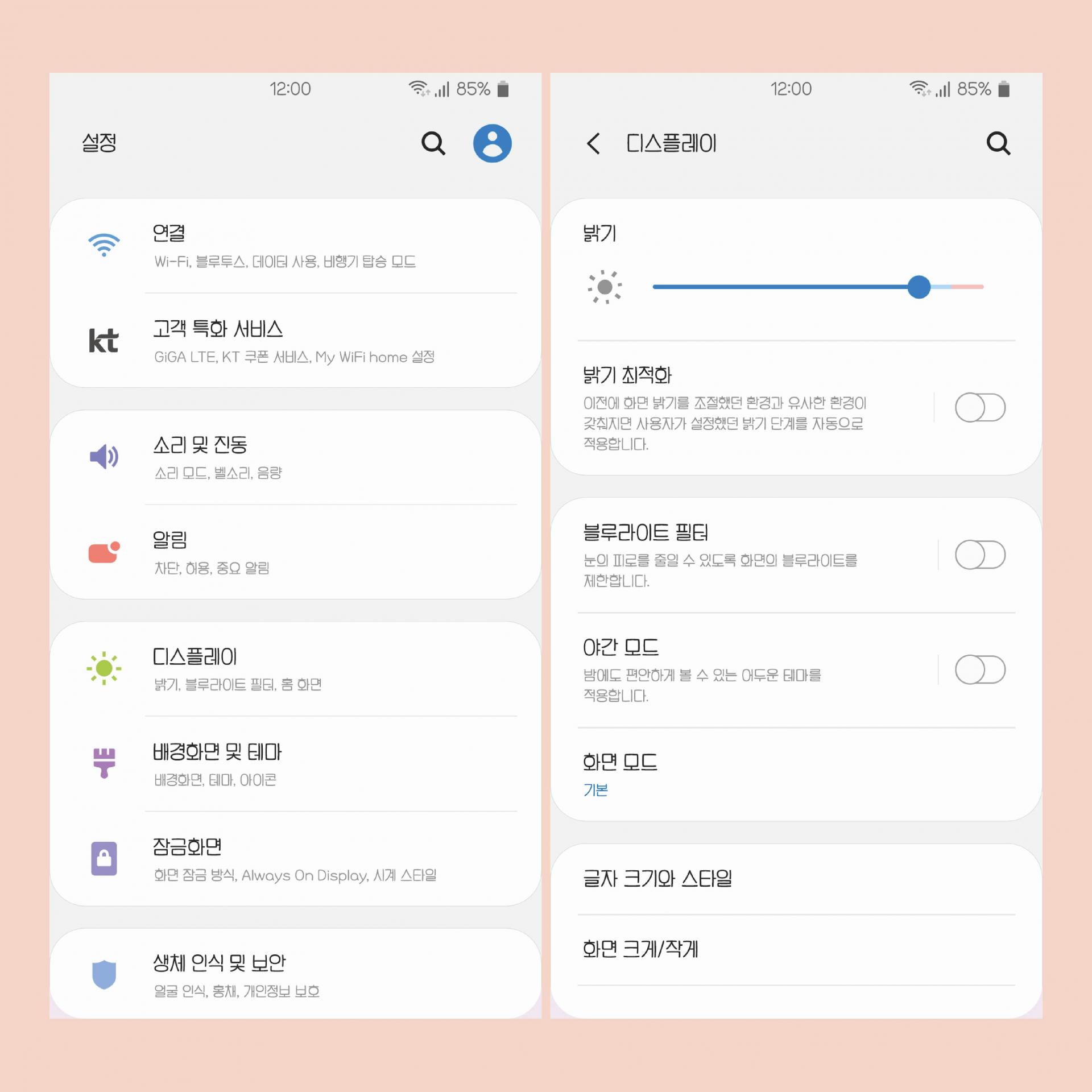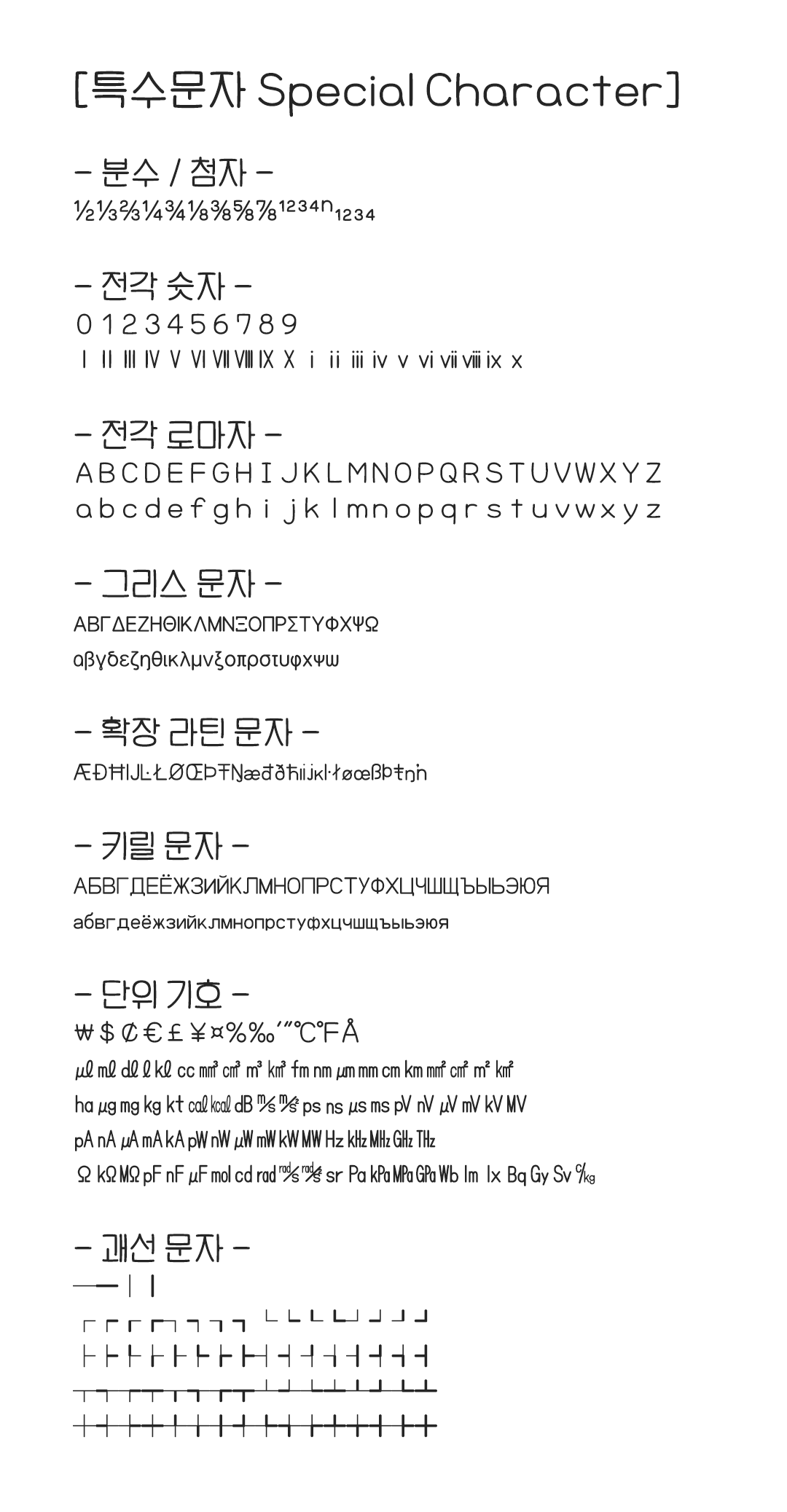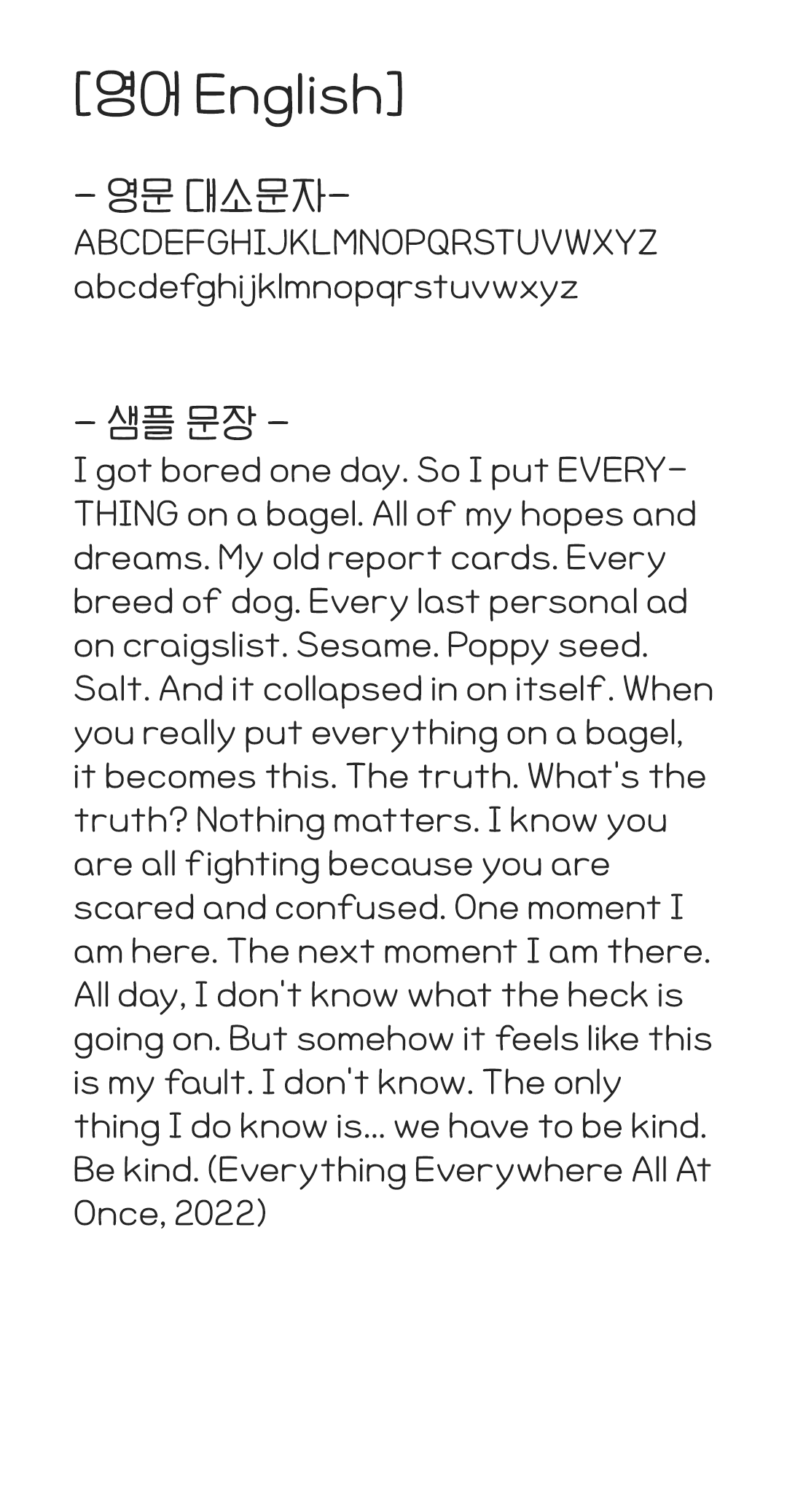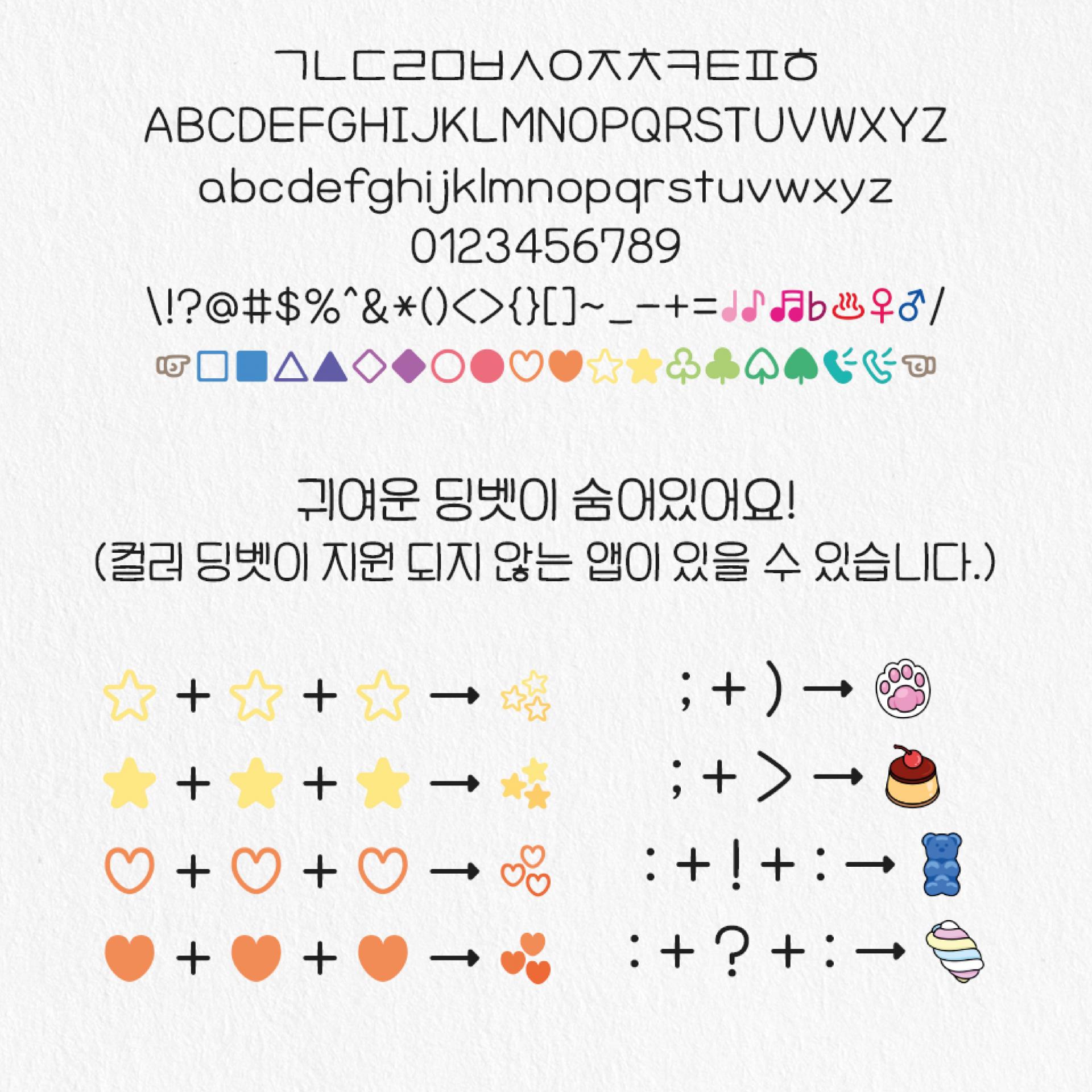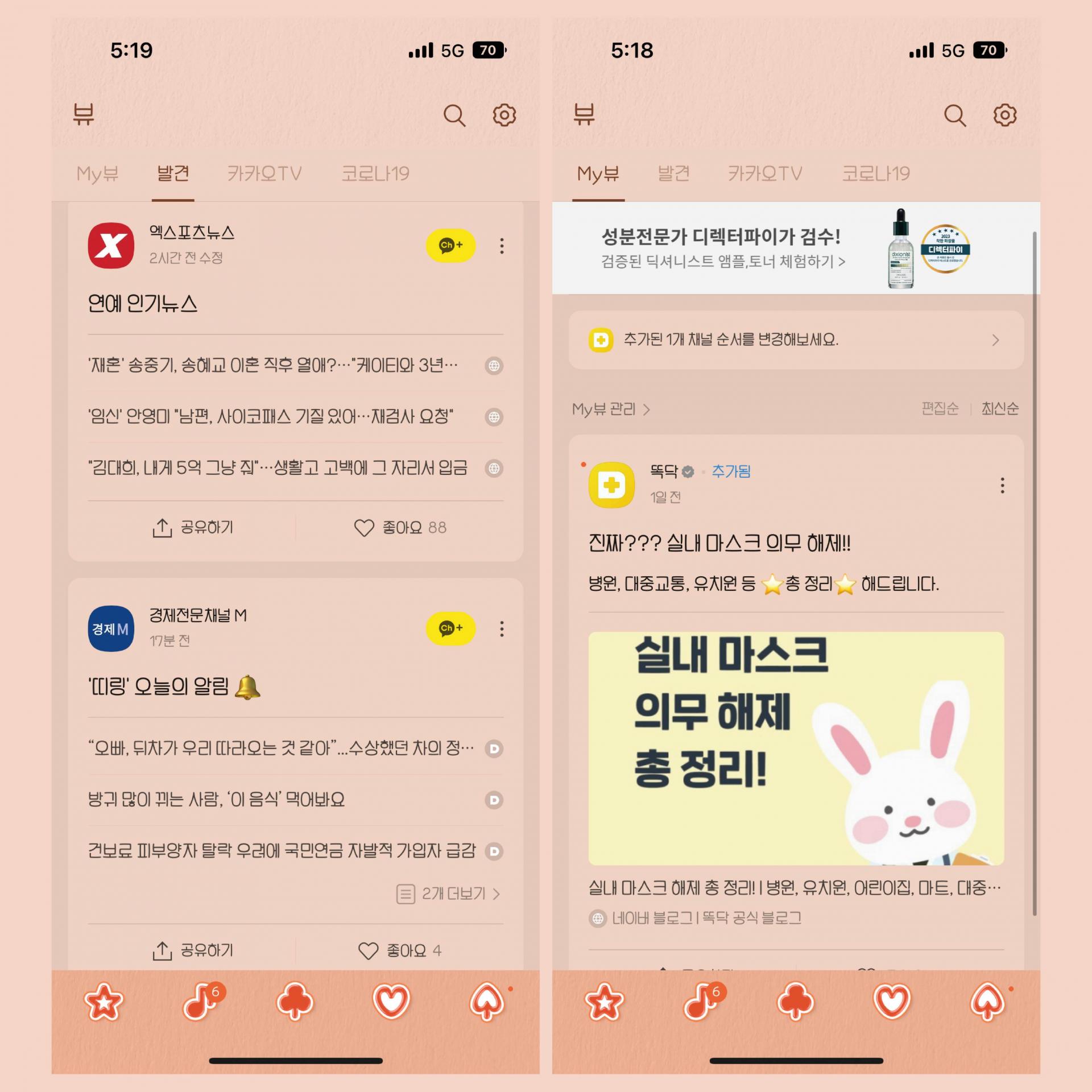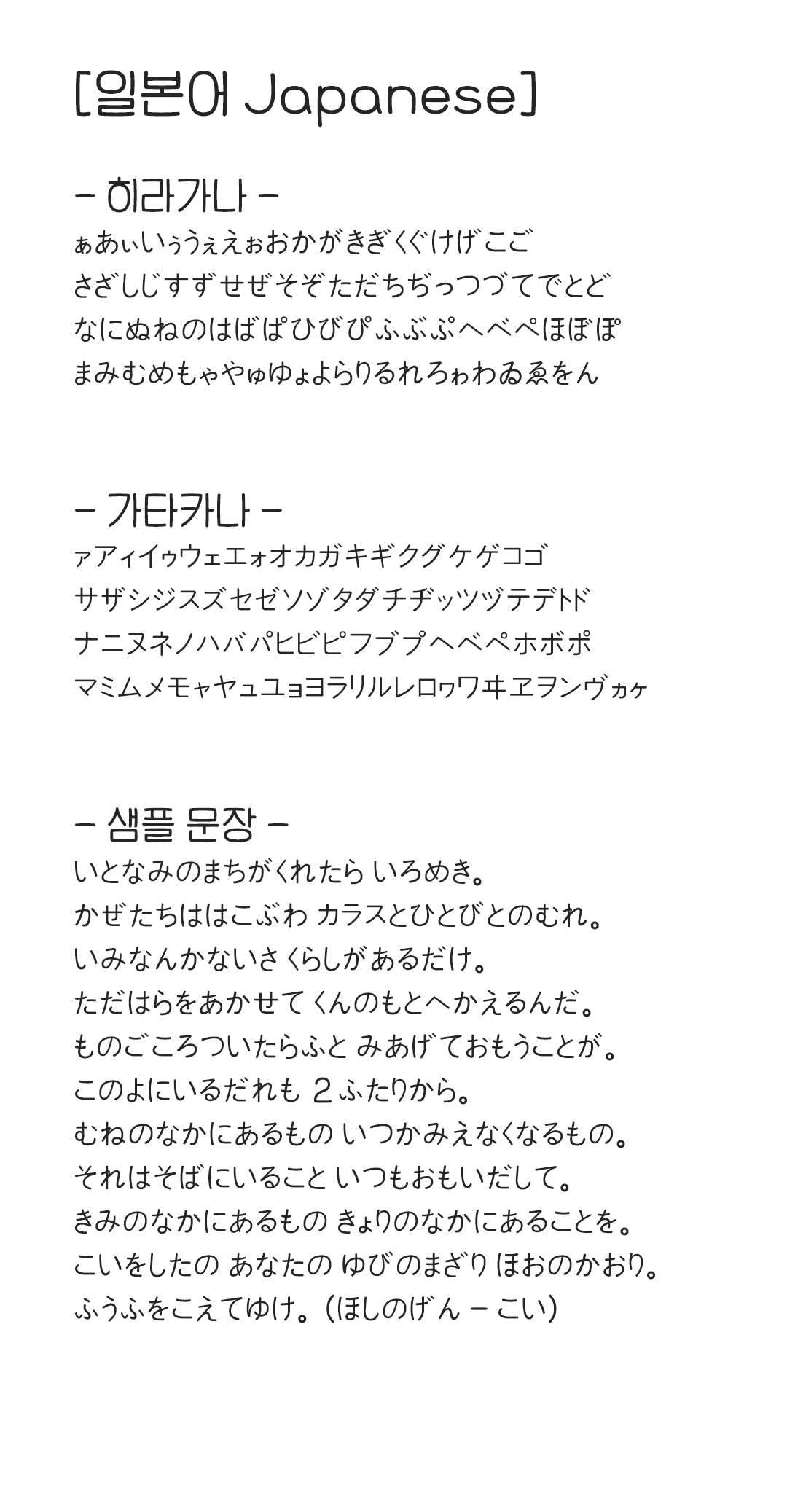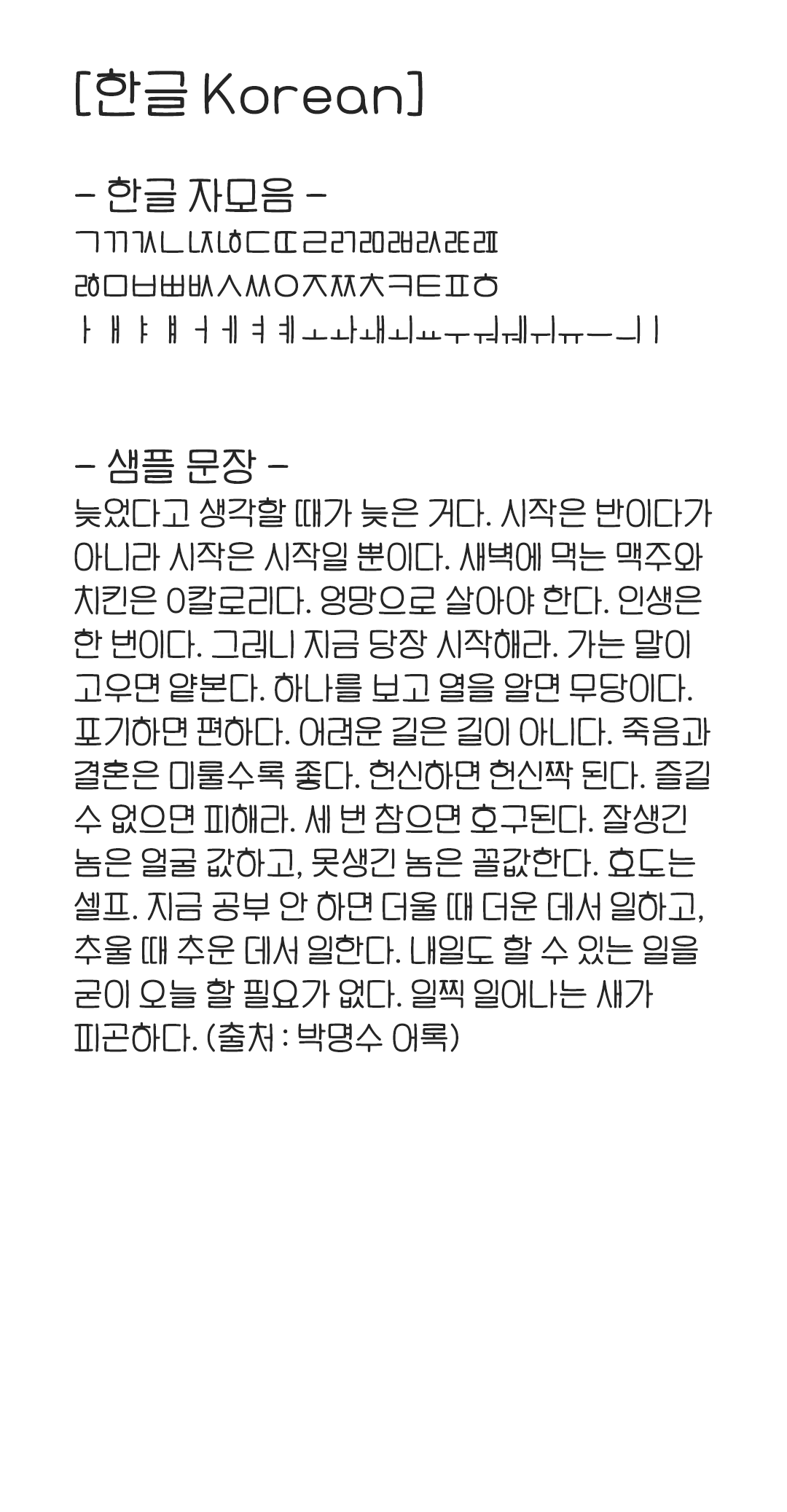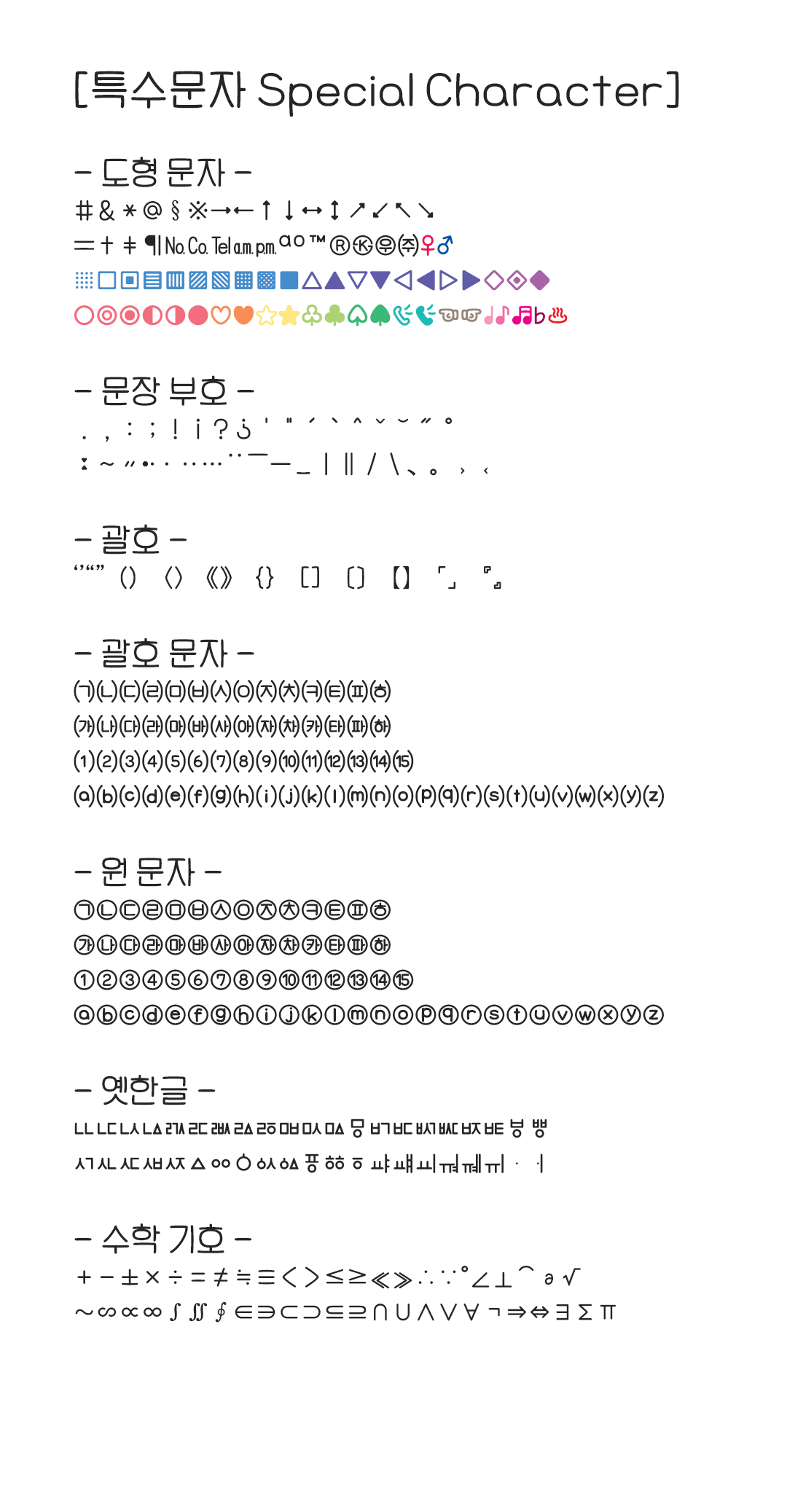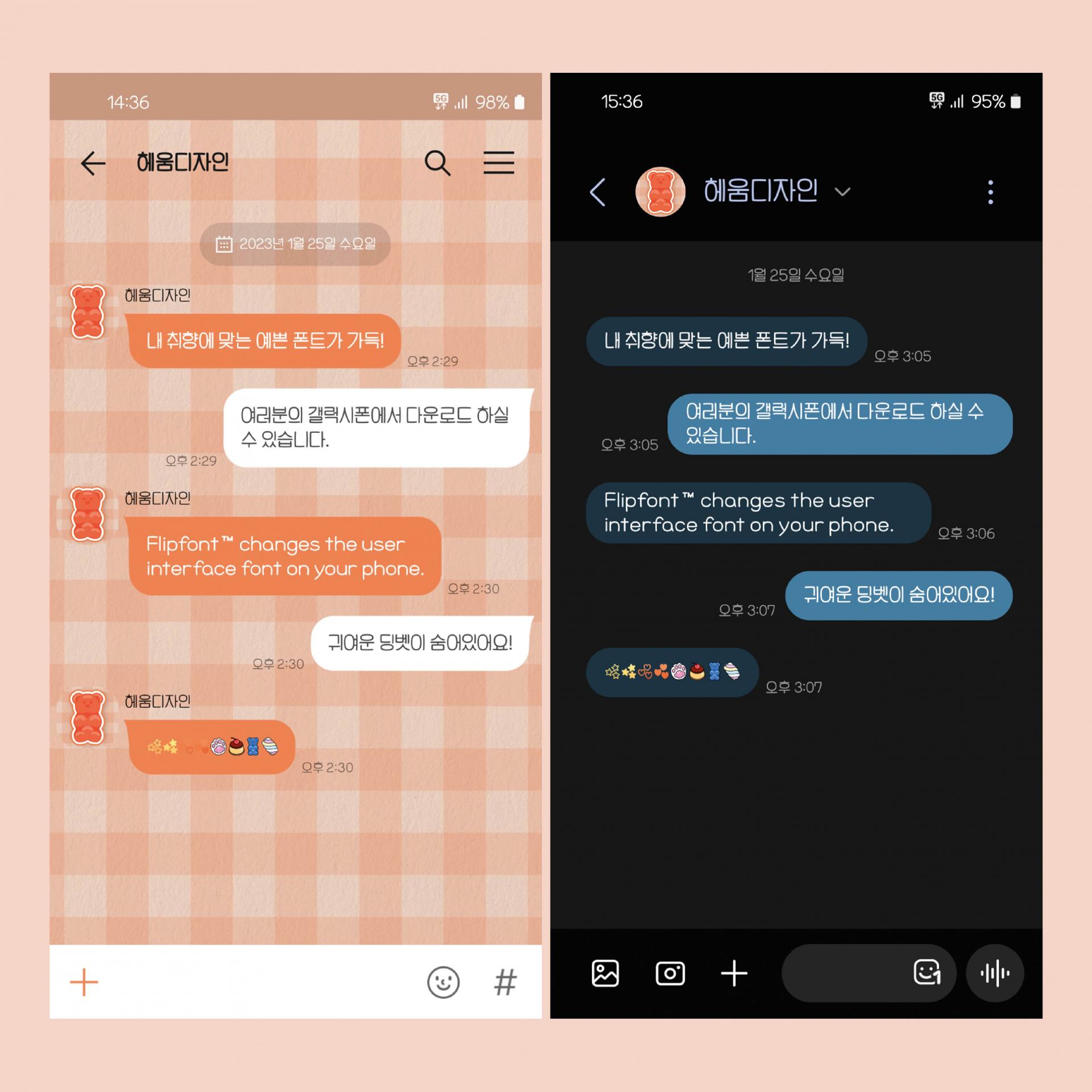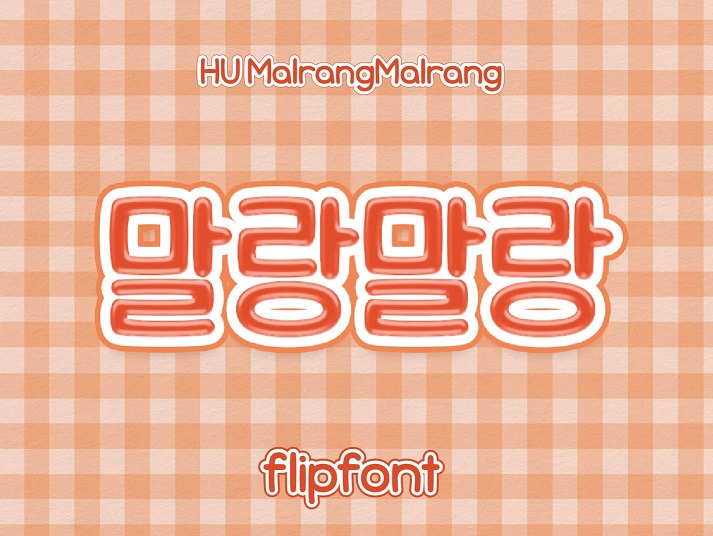
기존 상용서체로 출시 되었던 HU말랑말랑이 모바일폰트로 출시 되었습니다 !
둥글고 부드러운 느낌의 폰트입니다
(안드로이드 적용 예시 이미지입니다.)
(아이폰 적용 예시 이미지입니다.)
기존 상용서체로 출시 되었던 HU말랑말랑이 모바일폰트로 출시 되었습니다 !
둥글고 부드러운 느낌의 폰트입니다
(안드로이드 적용 예시 이미지입니다.)
(아이폰 적용 예시 이미지입니다.)